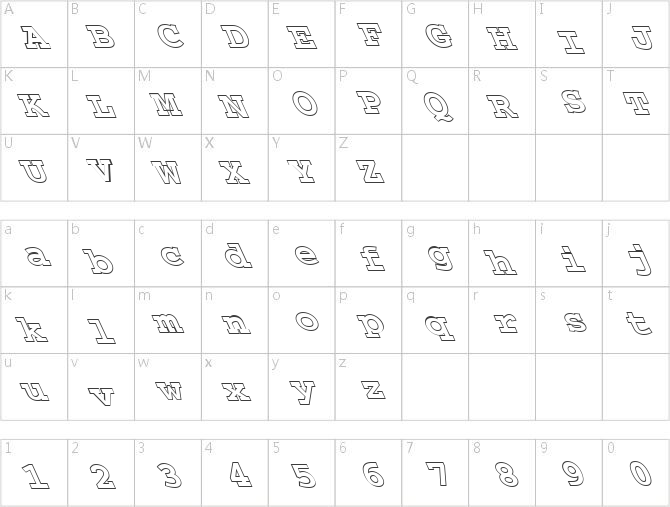
FZ BASIC 54 HOLLOW LEFTY
FZ BASIC 54 HOLLOW LEFTY介紹
FZ BASIC 54 HOLLOW LEFTY字體字庫是一款讓人賞心悅目、百看不厭的英文字體,適合各類廣告和產品包裝設計應用,字體大小0.08MB,格式為ttf字體,上傳用戶是瀨子,作者/版權方為未知